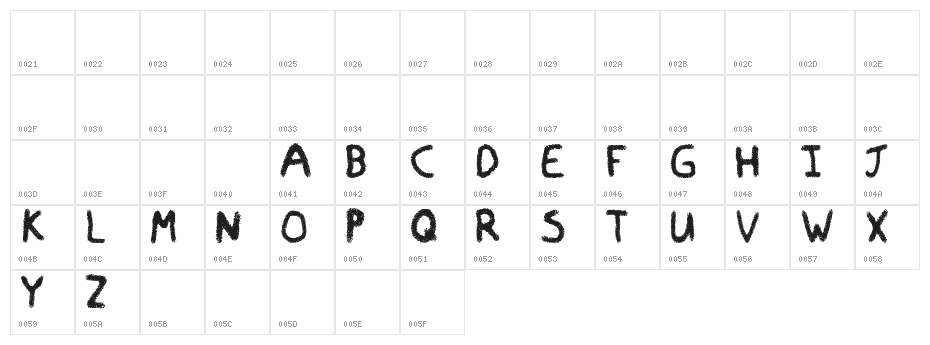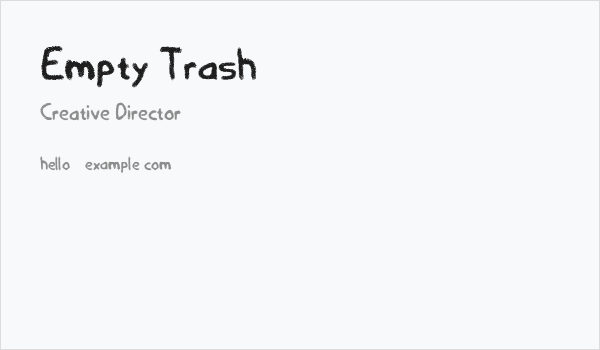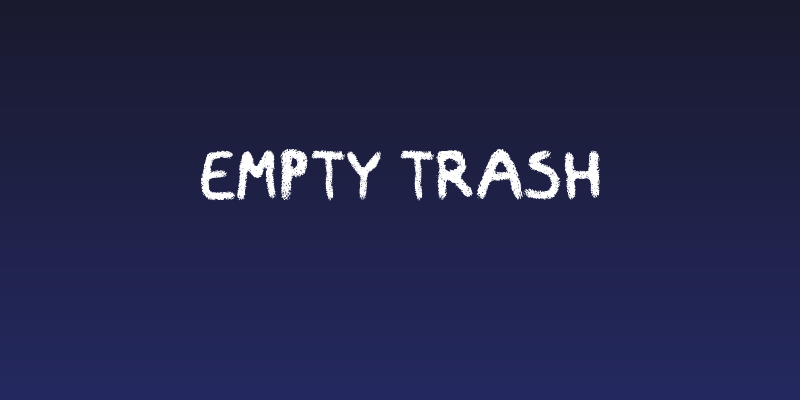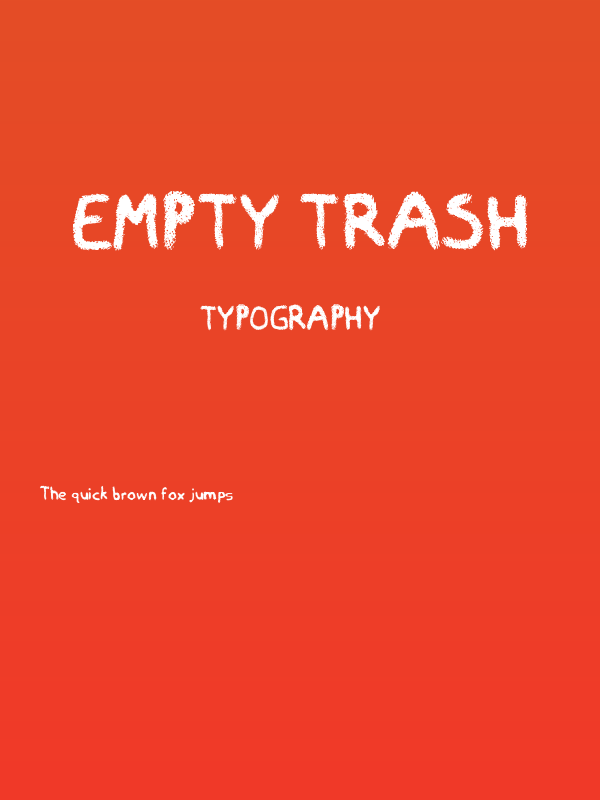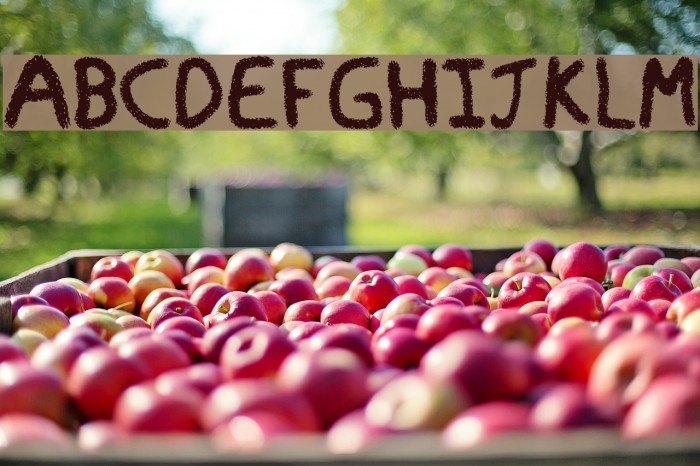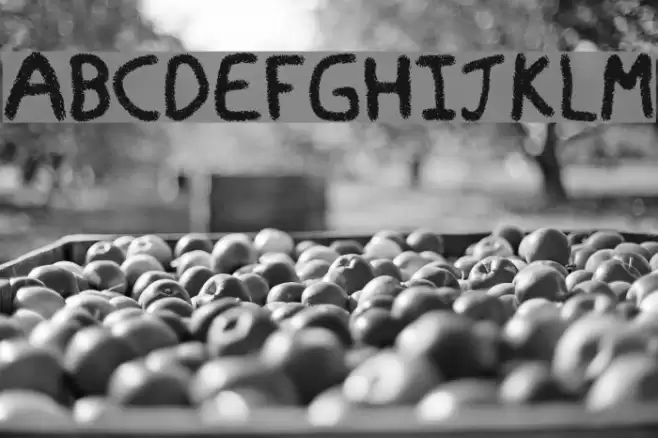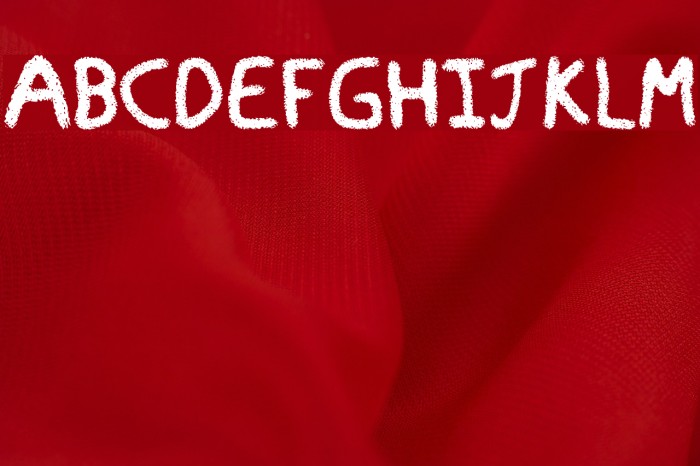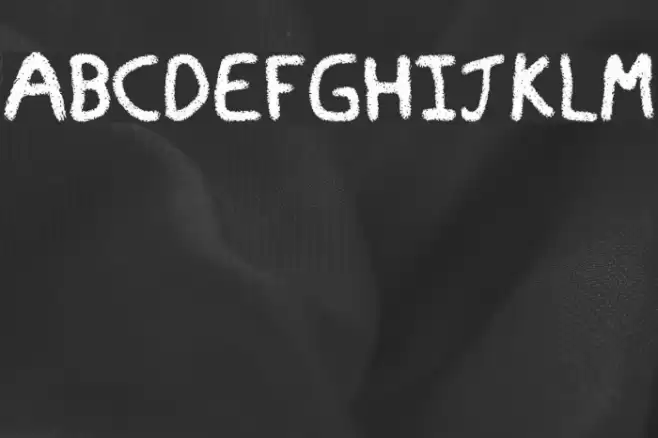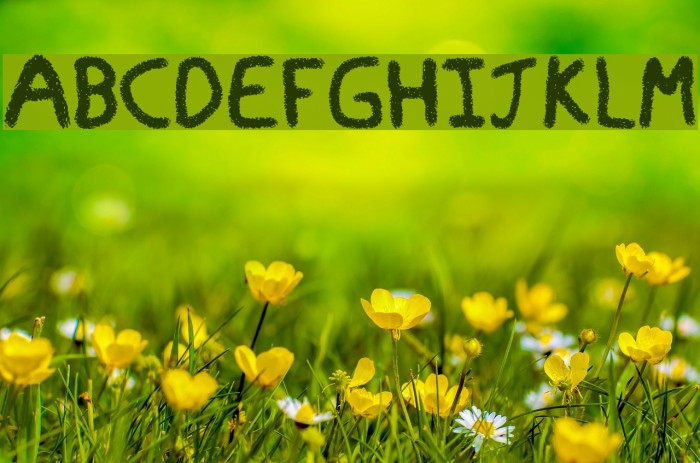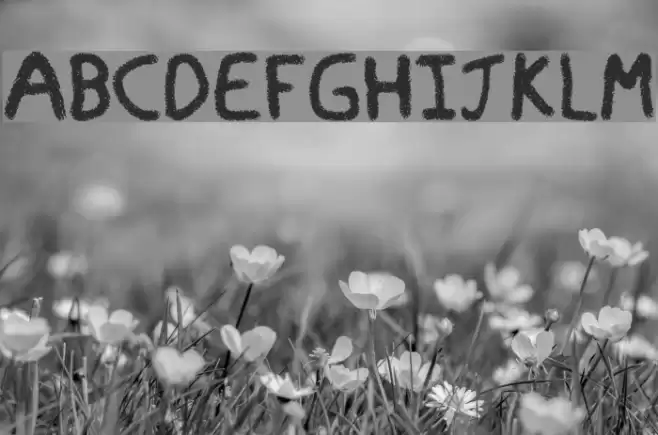
Empty Trash Font
| 全体的なスタイル | Playful, Artistic |
| おすすめプロジェクト | Ideal for children's book covers, playful posters, creative branding, and artistic invitations. |